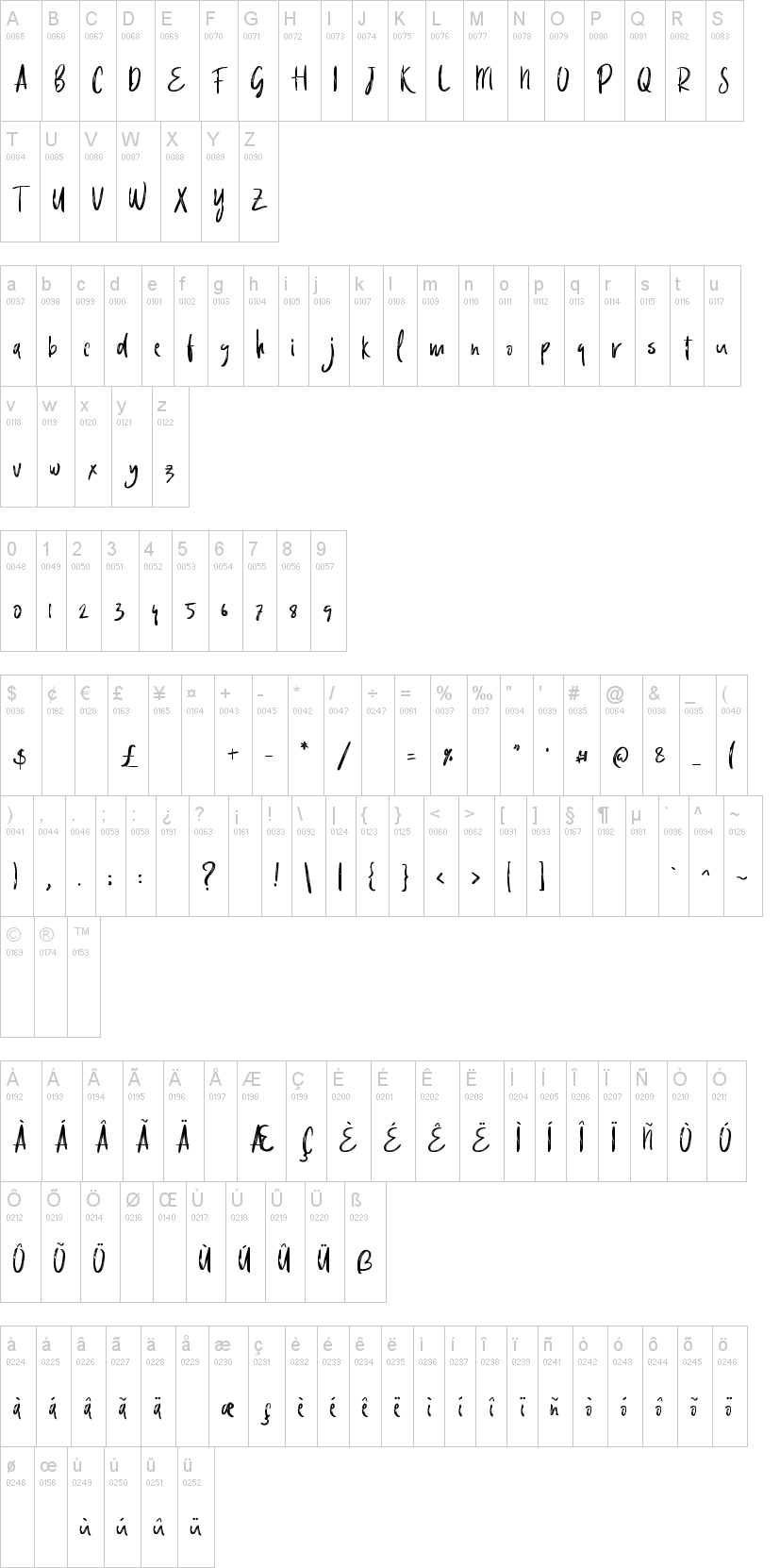
Amsterdam字体是一款由荷兰设计师Lex de Haan设计的简洁明快的英文字体,它的字体风格介于现代和传统之间,具有清晰的细节和良好的可读性。它的设计灵感来源于荷兰的传统文化和建筑,具有传统的荷兰风格,同时也具有现代感。Amsterdam字体拥有完整的字母表,包括大小写字母、数字、标点、符号和特殊字符,能够满足各种不同的文字需求。内容介绍
Amsterdam是一款非常不错的手写艺术字体,具有很好的视觉感,适合于文化类的宣传设计、商业类品牌的广告和产品包装设计以及个性化文字排版等较多场景。